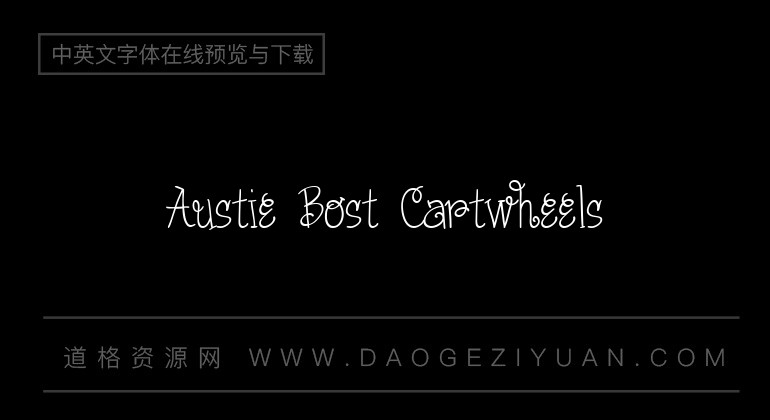
Austie Bost Cartwheels 是一种手写风格的漂亮字体,其设计灵感源自于纸张上的手写文字。这种字体的特点是有很多装饰性的笔画和花纹,非常适合用于卡片、海报、手写风格的设计等。Austie Bost Cartwheels 字体的字母和数字都非常有个性,非常适合用于需要突出个性和独特性的设计项目。同时,这种字体的可读性也非常好,可以用于各种不同的场合。总的来说,Austie Bost Cartwheels 字体是一种非常富有创意和个性的字体,可以为设计师带来很多灵感和想象力。内容介绍
Austie Bost Cartwheels是一款非常不错的手写艺术字体,具有很好的视觉感,适合于文化类的宣传设计、商业类品牌的广告和产品包装设计以及个性化文字排版等较多场景。